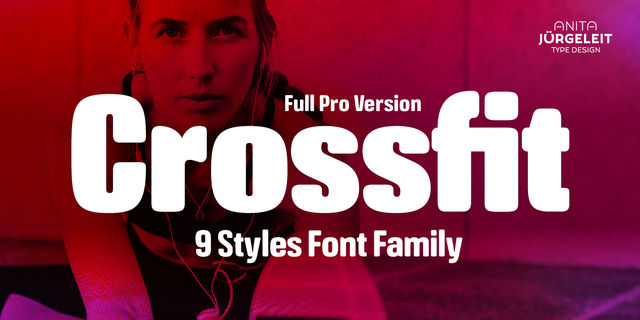
Crossfit – это новое семейство заголовочных шрифтов. Идеально для набора текстов крупным кеглем. Например, больших киноафиш, рекламных или редакционных заголовков. Может подойти таким темам: спорт, приключения, суровая природа и самые разнообразные сложные жизненные ситуации. Его смелость и стабильность превратит ваше творение в дизайн, качество которого не подлежит сомнению. Crossfit смелый, чистый и в то же время дружелюбный, благодаря закругленным углам.
Шрифтовое семейство Crossfit содержит 9 начертаний в 8 вариантах насыщенности: hairline, thin, light, roman, demi, bold, black, heavy.
OpenType функции: sub и superscript, nominator и denominator, fractions, ordinals.
Шрифтовое семейство Crossfit поддерживает 90 языков, в которых используются латинские символы. Шрифт разработала Анита Юргелейт в 2019 году.